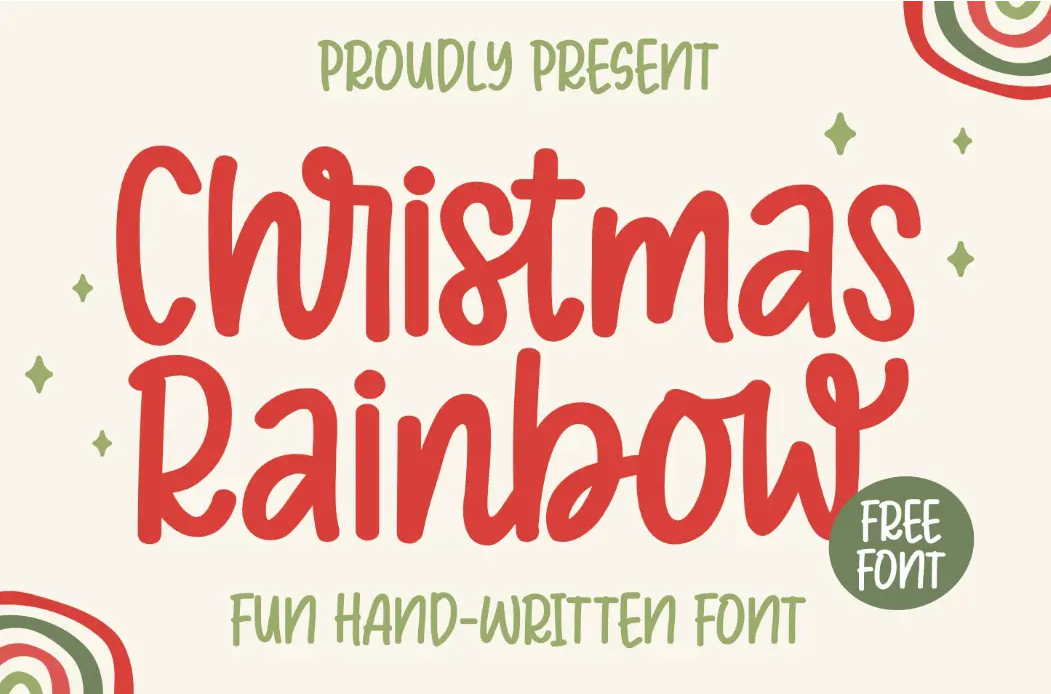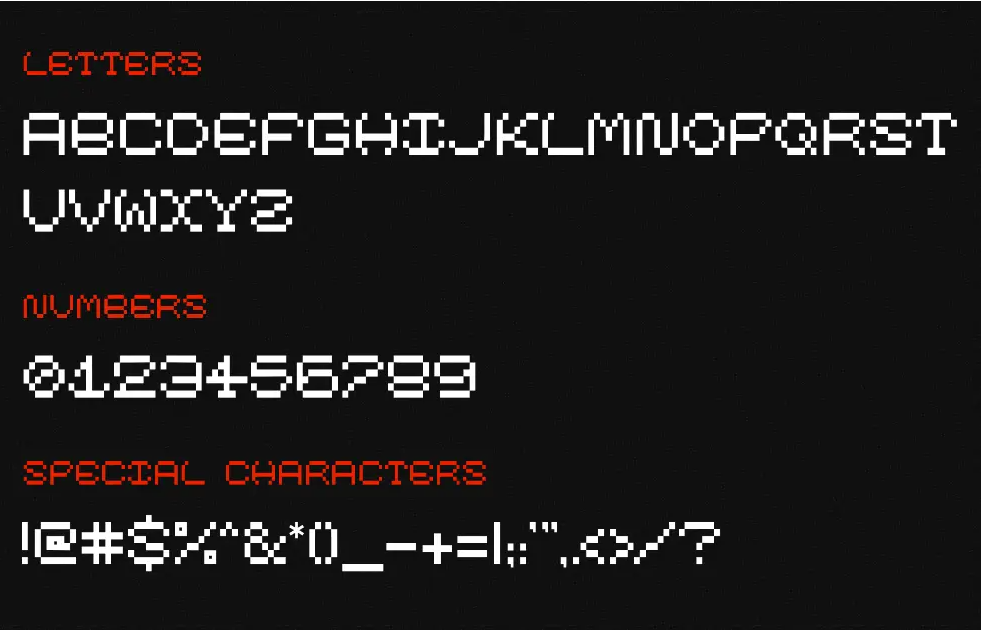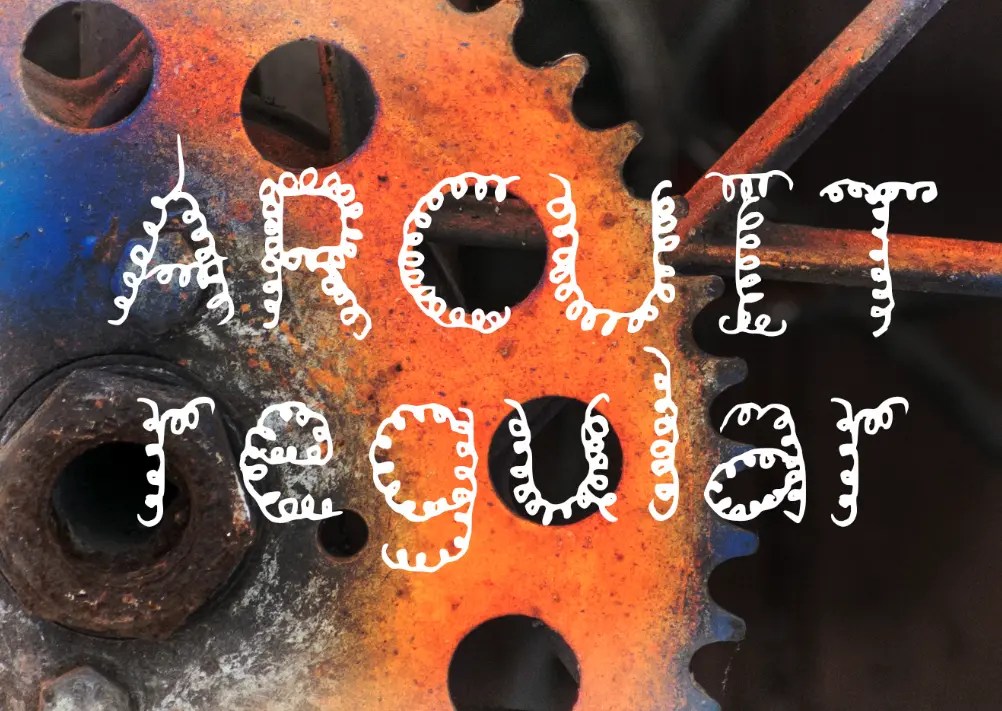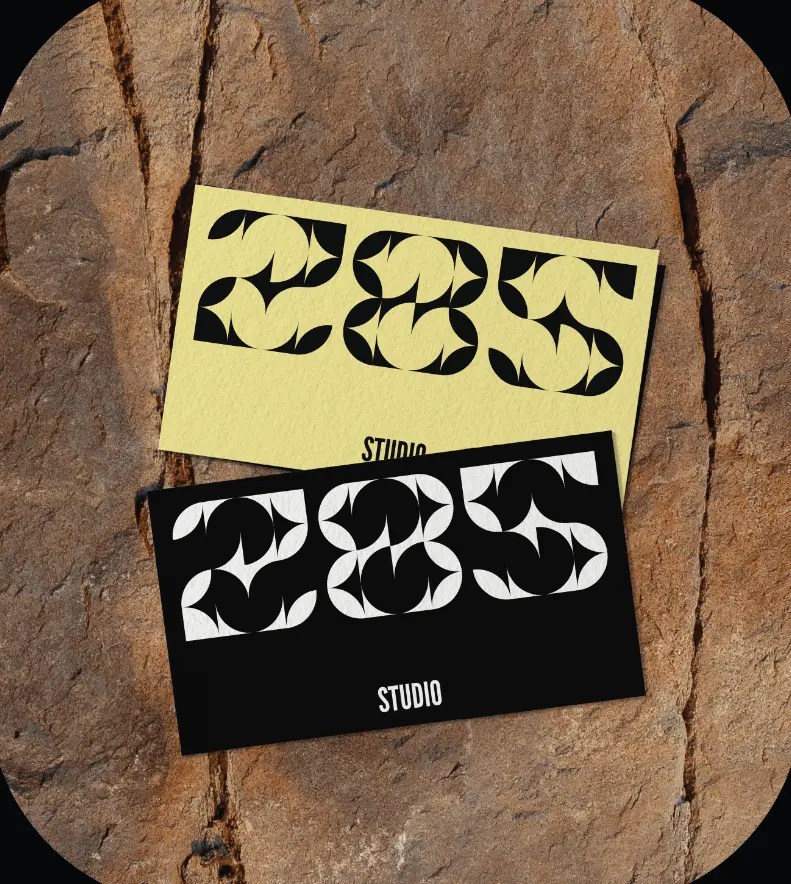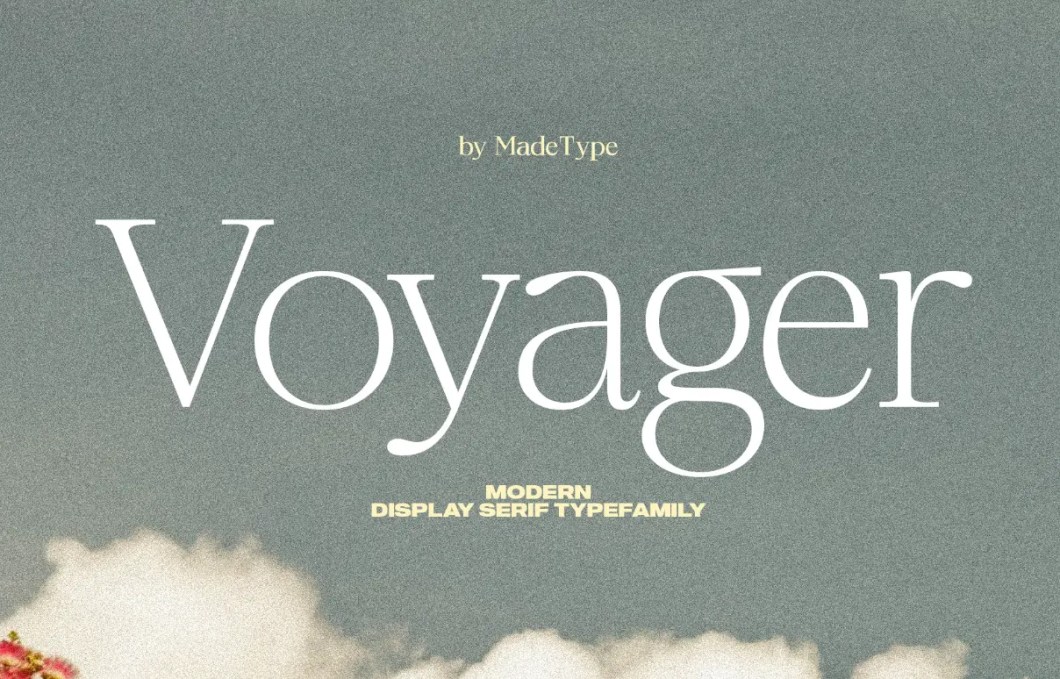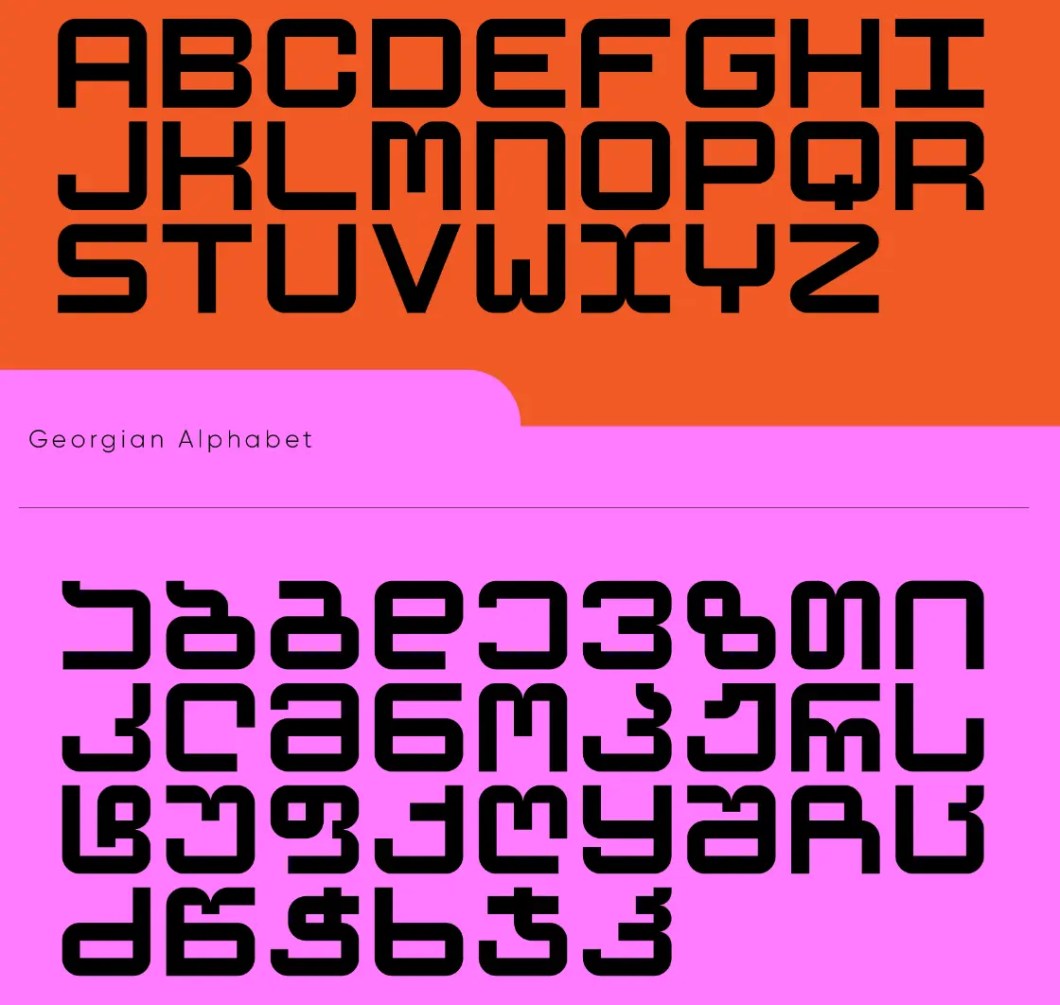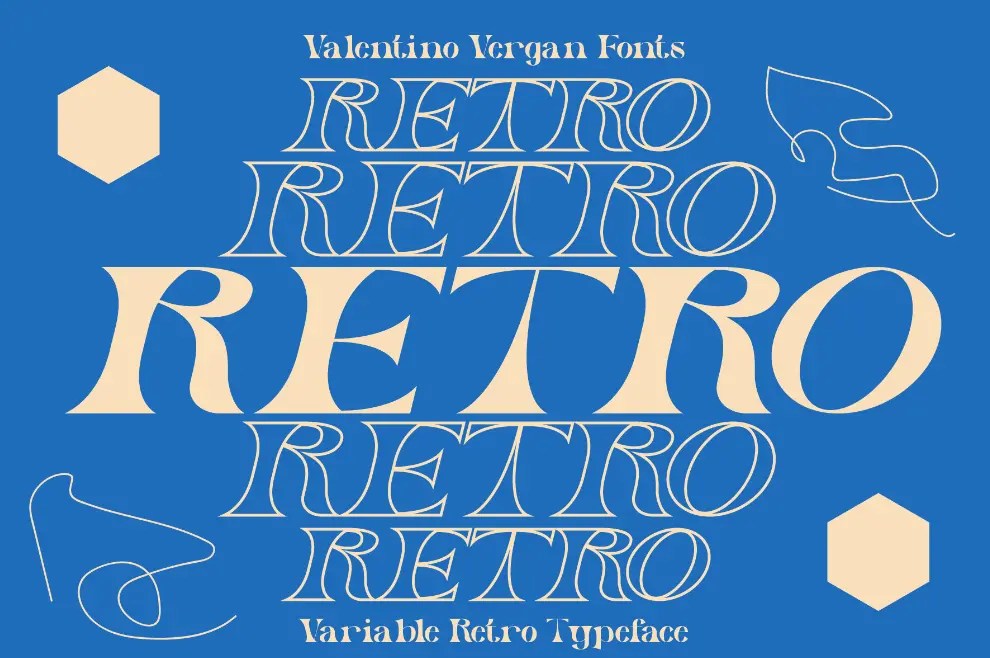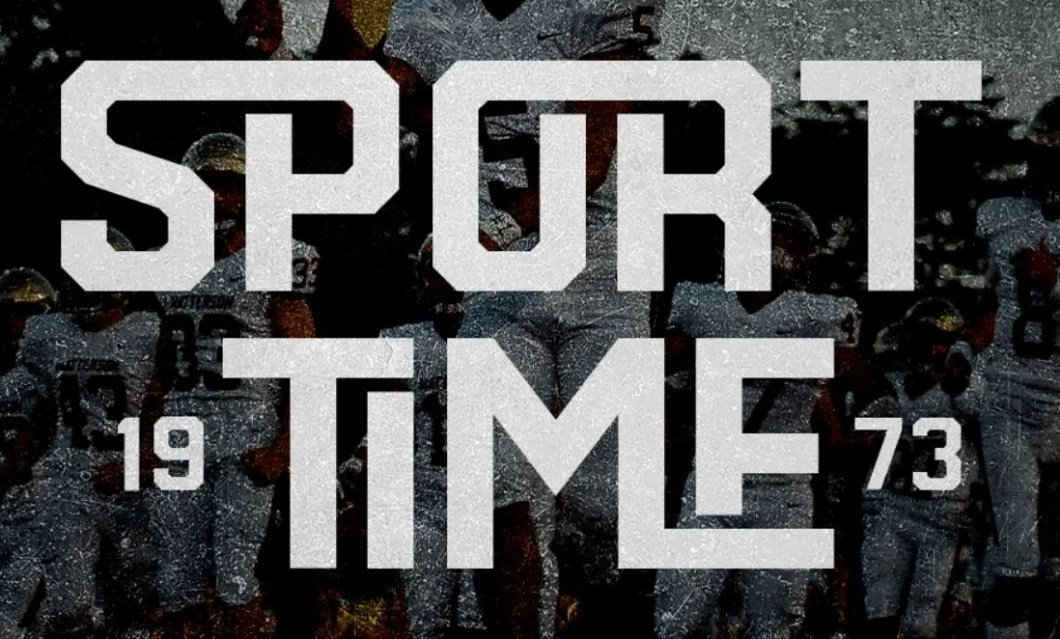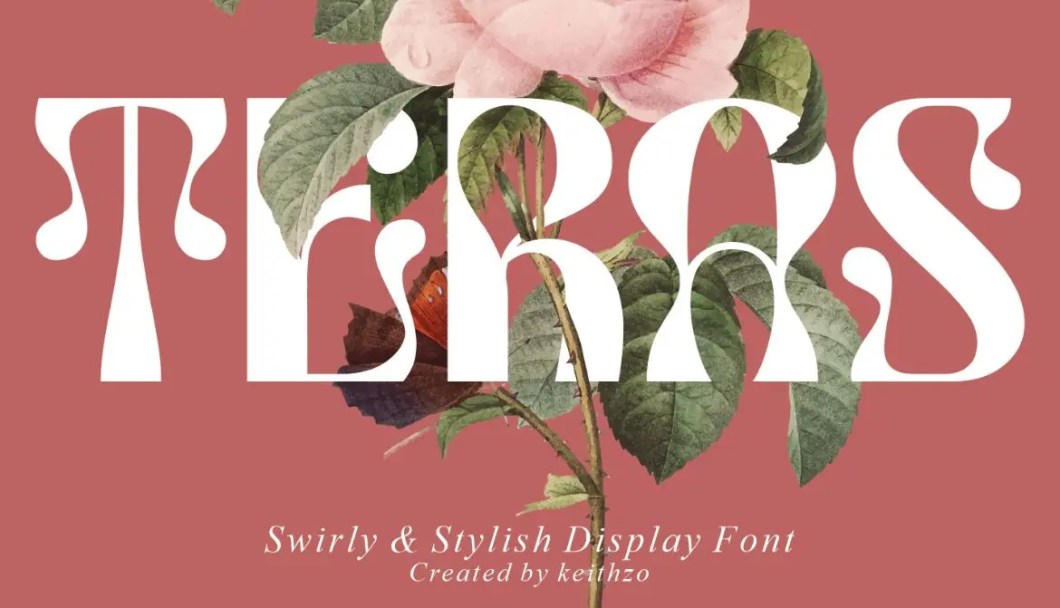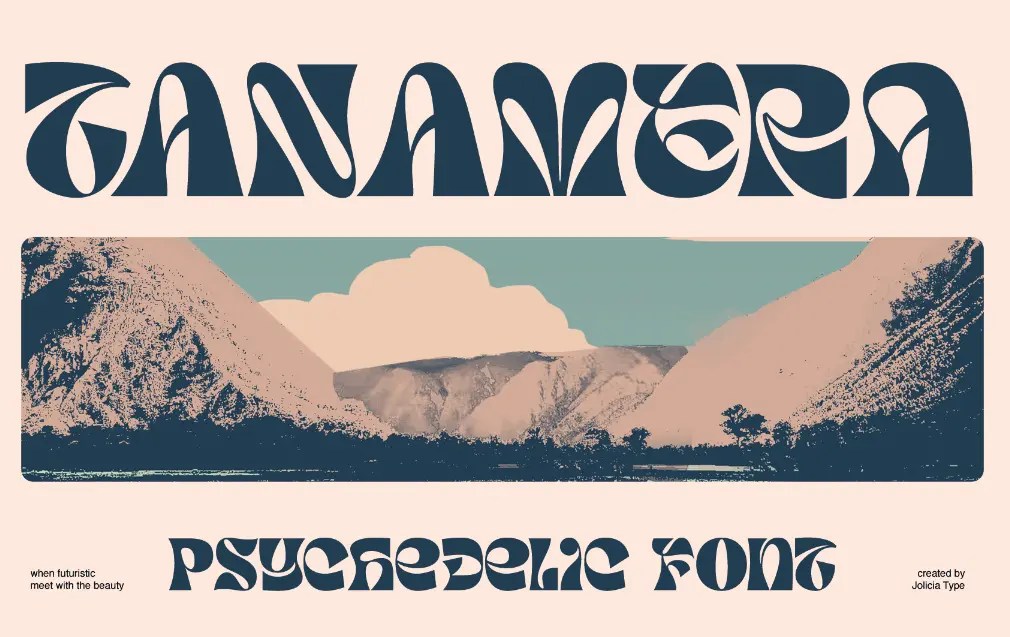
50+ beste freie Fonts
Planen Sie eine sofortige Änderung für Ihr nächstes Website-/App-/Grafikdesign? Nun, die neueste Sammlung von kostenlosen Schriftarten und Typografien für Grafikdesign könnte die ultimative Antwort auf Ihr Anliegen sein.
Egal, ob Sie ein Fan der einfachen serifenlosen Schrift oder des traditionellen Typs der modernen serifen sind, es gibt einfach viele kostenlose Schriftarten-Optionen zur Auswahl.
Charming Christmas Rainbow Handwritten Font
Fügen Sie Ihren festlichen Designs mit der bezaubernden Christmas Rainbow-Schriftart einen spritzigen Farbtupfer hinzu. Diese verspielte Display-Schriftart verfügt über ein Regenbogenspektrum von Farben für jede Buchstabenform und verkörpert den verspielten Geist der Weihnachtszeit. Der luftige, handgeschriebene Stil mit geschmeidigen Linien schafft einen warmen, freundlichen Look – ideal, um Weihnachtsfreude zu verbreiten.
ModernPixel Font
Ein moderner Pixel-Schriftart kostenlos für den persönlichen und kommerziellen Gebrauch.
Arcuit Regular Handwritten Font
Eine kreative, handgeschriebene Display-Schriftart, inspiriert von Stacheldraht oder Metallfedern.
Tanamera Psychedelic Font
MS BLOCK Free Font
MS Block ist eine Display-Schriftart mit gleicher Breite und Höhe für jeden Buchstaben. Enthält das georgische und lateinische Alphabet. Kostenlos für kommerzielle und redaktionelle Zwecke.
MADE Voyager Font
Eine moderne Display-Serifenschriftfamilie, perfekt für Poster, Flyer, Karten, Magazine, Bücher und mehr.
Briar Free Display Font
Eine moderne Display-Schriftart, inspiriert von Blumen und Geometrie.
PixelType Pixel-style Font
Pask Variable Retro Font Family
Eine von Retro inspirierte variable Schriftfamilie. Pask hat einen hohen Kontrast und eine dünnen Haarlinie, dies verleiht der Schriftart ein kühnes und retro Aussehen. Pask kommt mit eigenständigen Schriftarten und einer variablen Version, die variable Version ermöglicht es Ihnen, die Breite und den Schrägstrich anzupassen.
Witch Free Typeface
Kostenlose Hexenschrift für Halloween-Designs.
Romántica Font
Vintage Museum Display Font
Eine Vintage-Serifen-Display-Schriftart.
Teras Display Font
Eine stilvolle und geschwungene Display-Schriftart.
Zeviero Font
Eine stilvolle Serifenschrift kostenlos für den persönlichen Gebrauch.
Sport Time Font
Eine moderne sportliche und universitäre Schriftart.
TRIBE Font Free Download
Hyper Blob Font
Die Hyper Blob-Schriftart ist eine einzigartige und vielseitige Display-Schriftart, die ein Blasenmuster mit einem Graffiti-Thema kombiniert. Sie bietet eine Reihe von Funktionen, darunter Groß- und Kleinbuchstaben, alternative Zeichen, Ligaturen und mehrsprachige Unterstützung, was sie zu einer äußerst vielseitigen Option für jedes Designprojekt macht. Egal, ob Sie an einer Marketingkampagne, einem Webdesign oder einem anderen kreativen Projekt arbeiten, diese Schriftart bringt Ihre Ideen garantiert zum Leben.
Monobloco Free Monospaced Font
IL Zeit free Font
Eine kostenlose Schriftart, die Vintage-Inspiration mit modernen Designelementen kombiniert und eine wirklich einzigartige und auffällige Schriftart schafft. Inspiriert von der ikonischen SHARP EL-808-Rechenmaschine verfügt IL Zeit über neu gezeichnete Zahlen, die den unverwechselbaren Look dieses klassischen Handgeräts perfekt einfangen. Neben den Zahlen enthält die Schriftart auch die Buchstaben a, b, c, d, f und h, die auf dem segmentierten Design des Taschenrechners basieren und der Schriftart einen schlanken und modernen Look verleihen.